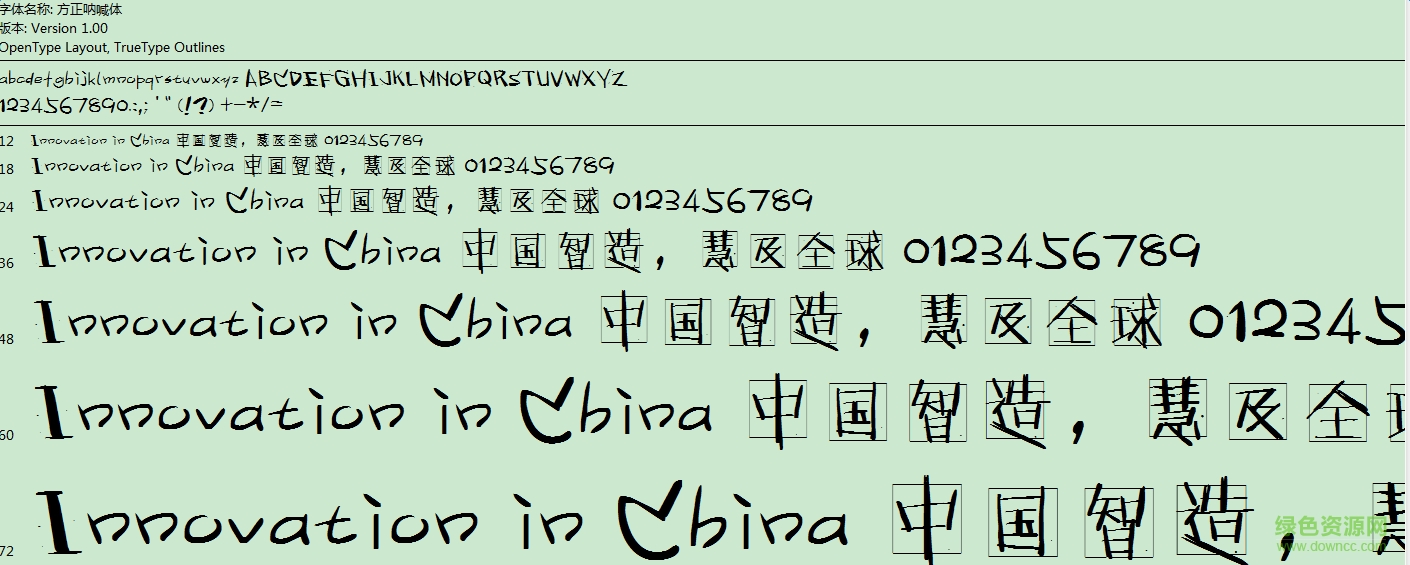
fznht字体又叫方正呐喊体,是一款非常有个性的广告字体,笔画棱角突出,特征鲜明,给人的感觉狂放不羁,可以用在表情包制作、弹幕以及海报设计等方面,欢迎下载体验!
1.这款字体的笔画刚硬狂野,与浮动的方框形成鲜明的对比,如一个人强烈试图挣脱某种困境。
2.风格激情沸腾,适用于励志类的广告和产品包装设计,以及社交网络的个性化用字。
3.方正呐喊体试图表达一种呐喊、自嘲、发泄的情感,来排解年轻人在网络生活中的负面情绪。